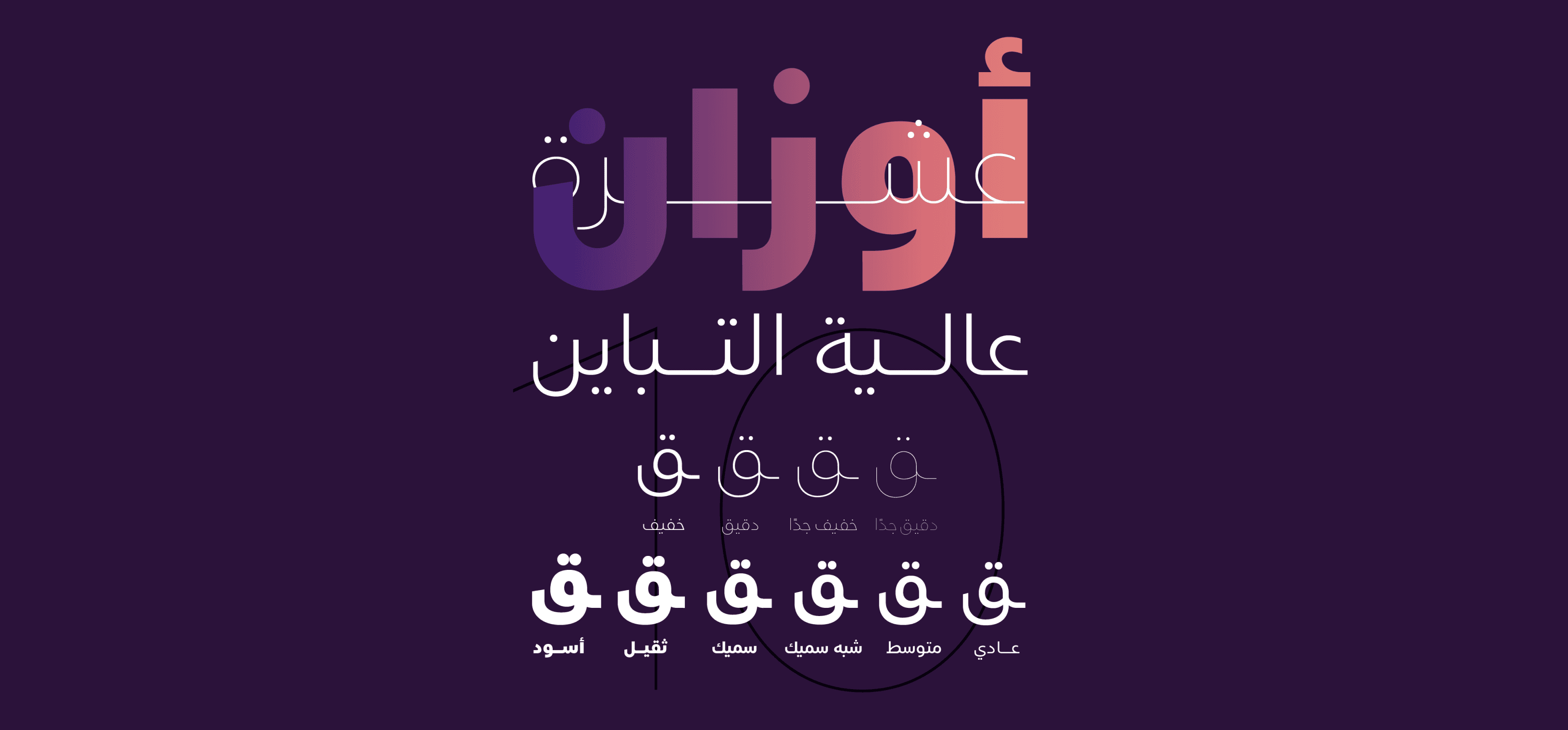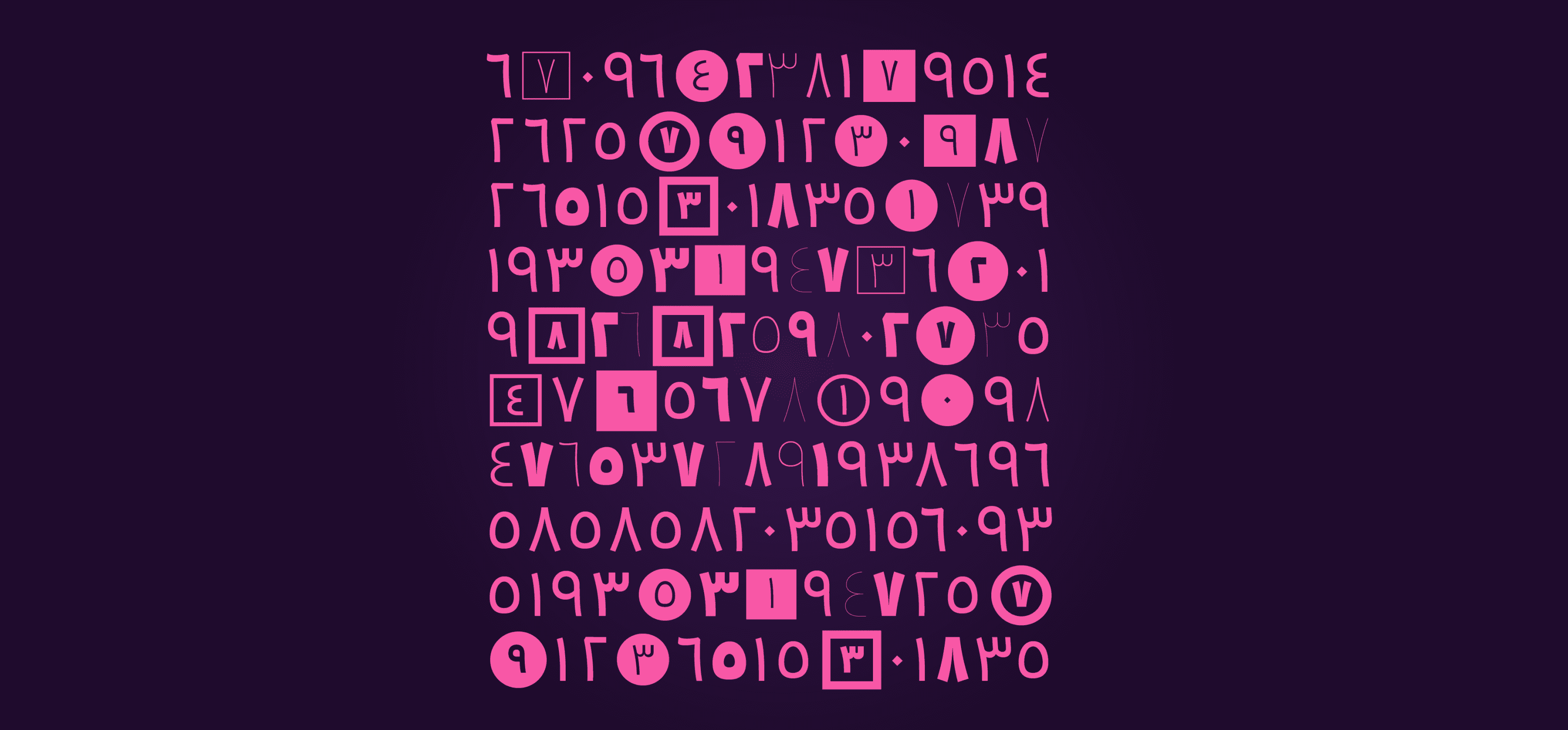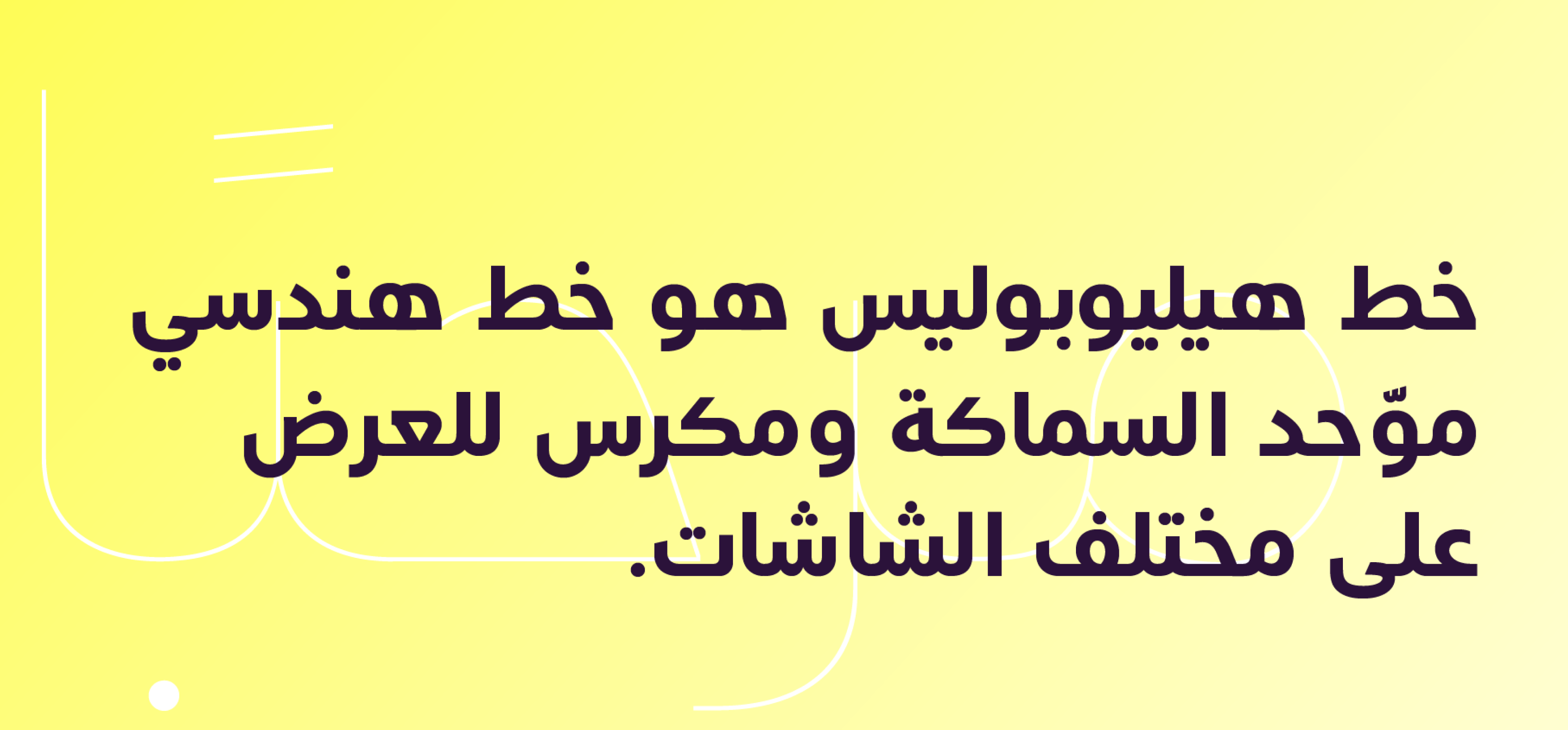
خط كوفي متعدد اللغات صُمم بعناية ليكون مثاليًا للشاشات والاستخدامات الرقمية.
يتميز بوضوح عالٍ في الأحجام الصغيرة، مع الحفاظ على جمالية استثنائية تتماشى مع تنوع التكنولوجيا الحديثة.
يأتي الخط بمظهر جديد كليًا، ويُوفر عدة أوزان متباينة تناسب مختلف الاستخدامات، مع حواف حادة وزوايا دائرية أنيقة تمنحه توازنًا بين القوة والرقي.